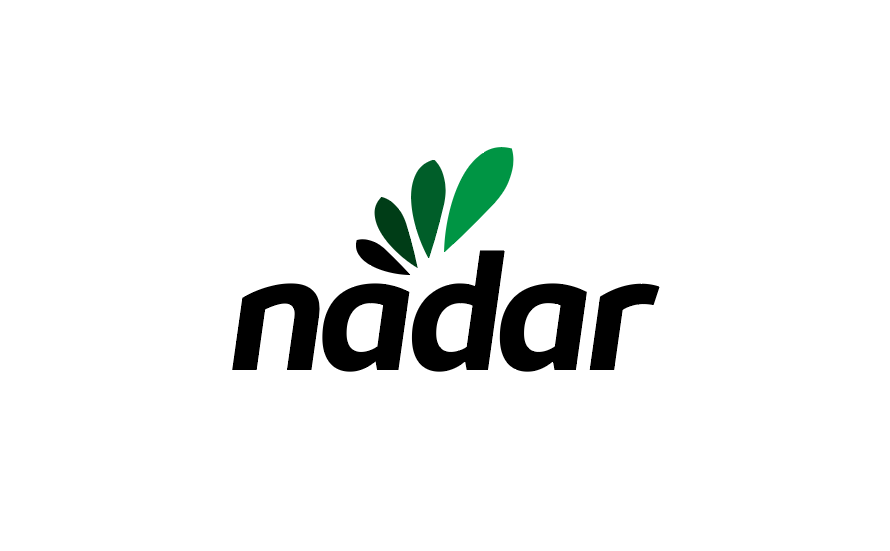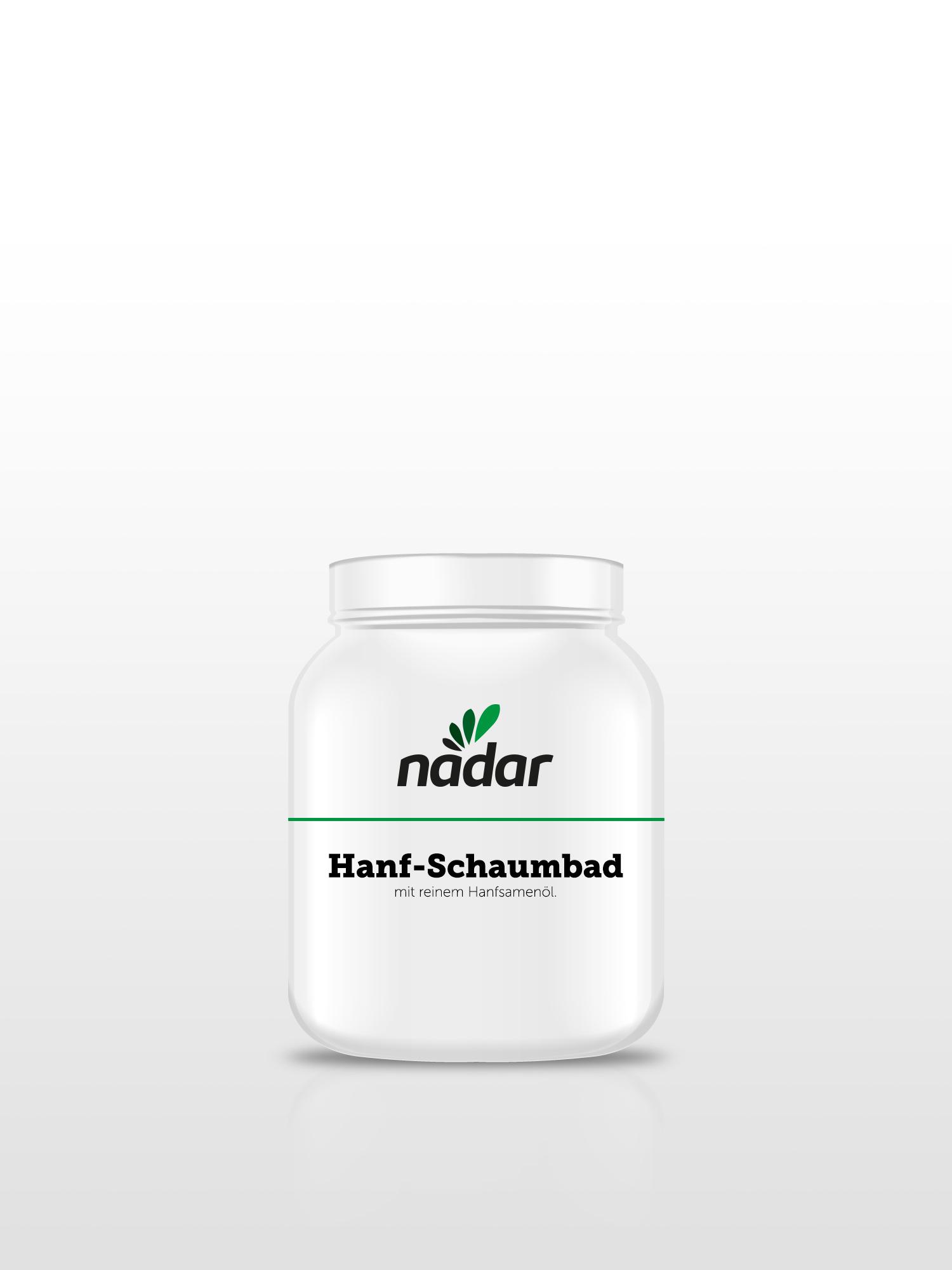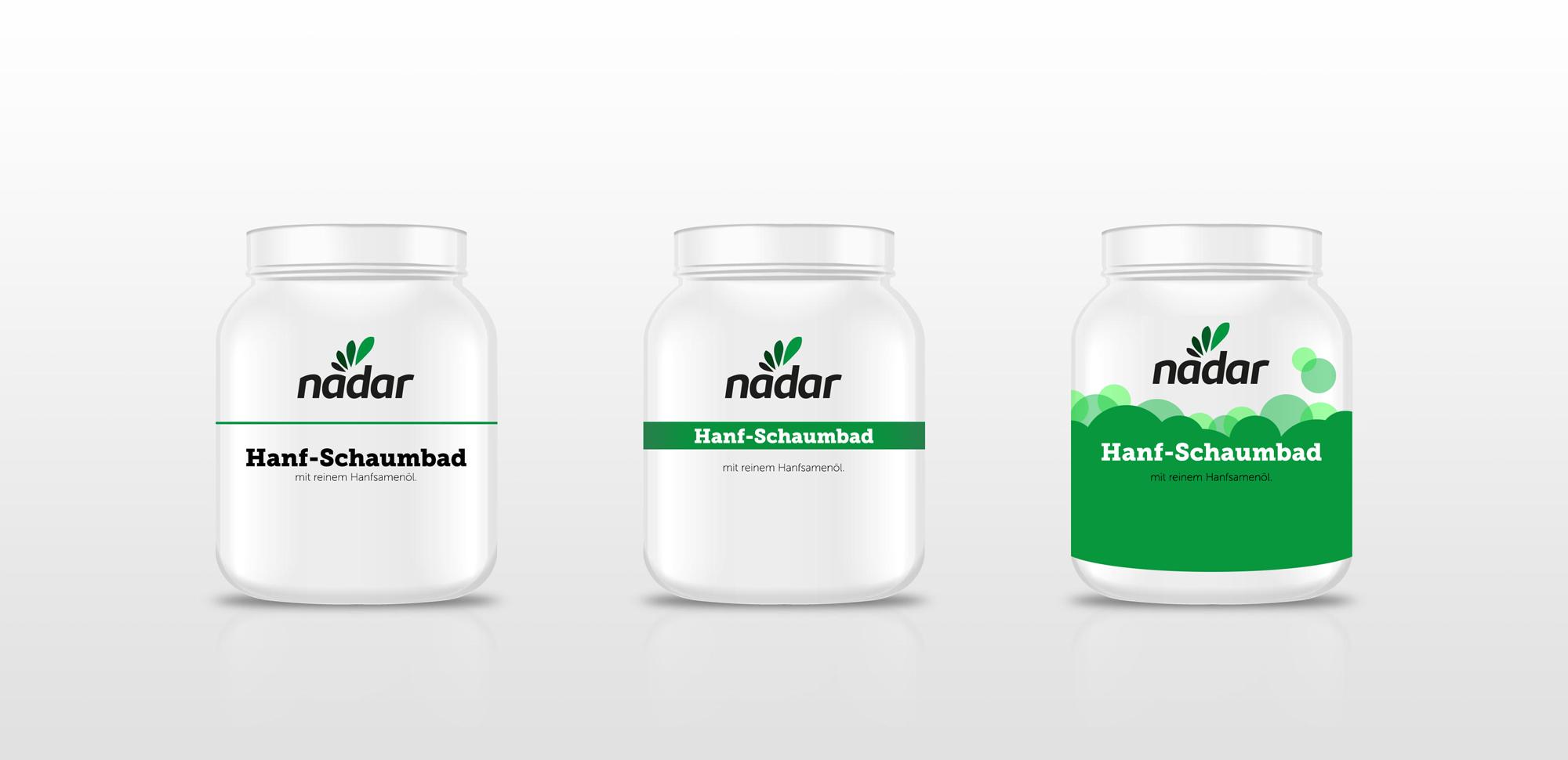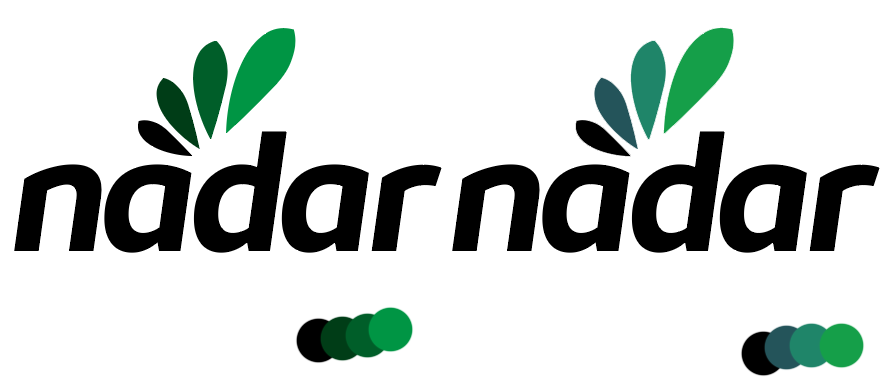
Suche eine mutige aber stimmige Ergänzung zu einem Logo
Ich suche eine passende Gebrauchsschrift zu meinem Logo-Entwurf. Ich würde gerne etwas mutiges nehme, bin mir aber nicht sicher ob ich nicht über das Ziel hinausschieße und meine Idee einfach nur schrecklich ist? ;-)
Die Schrift im Logo ist "Kabrio Bold Italic".
Mein Gedanke war jetzt, für Produktnamen der Firma, die Museo Slab Serif zu verwenden ... und für alles andere die Museo Sans.
Ich bin mir jetzt nicht mehr sicher ob ich mir die Museo nicht "schön geschaut" habe und würde mich über Feedback oder Alternativvorschläge freuen.
Aus vielen, vielen Verpackungen habe ich immer wieder gelernt, dass eine schmallaufende Schrift auf runden Behältnissen wesentlich glücklicher macht. Du kannst ja immer nur einen Ausschnitt unverzerrt lesen, und dieser ist wesentlich kleiner als von dir dargestellt. Mit einer so breiten Slab musst du die Schriftgröße zu klein wählen oder hast Umbrüche im Produktnamen.
Ich empfinde die Kombination  auf den 1., den 2. und den 3. Blick als sehr stimmig.
Ob und wie das auf Verpackungen funktioniert wird man eh probieren müssen. Die häufig verwendeten schmallaufenden Schriften für Kosmetikprodukte empfinde ich als schlecht les- und damit das Produkt als schlecht identifizierbar.
Die Museo kann ich auf Anhieb erkennen und lesen (auch ohne meine PC-/Lesebrille bemühen zu müssen). Und selbst wenn nur ein Teil des Produktnamens auf Anhieb sichtbar ist, steht das Produkt doch entweder in einem Warentypumfeld (Baden/Duschen) oder in einem Markenregal (nur nadar-Produkte) - ein kleiner Griff und ich weiss, worum es sich im Detail handelt.
Wenn diese klare Gestaltung für alle Produkte beibehalten wird, ist es für mich als Käufer kein Problem, in einem Drogeriemarkt z.B. »mein« Duschbad in kürzestmöglicher Zeit zu finden.
Bei mir hat es nur bis zum zweiten Blick standgehalten ;-)
Wobei ich mir nicht sicher bin, ob sich die beiden Schriften beißen oder ich ein Schaumbad nicht mit schwarzer, fetter Slab Serif zusammenkriege ..?
Vielleicht aber auch, weil beide Ebenen – Logo und Produktbezeichnung – schwer und fett sind, aber dann doch wieder anders. Wobei ich nicht empfehlen würde die Schrift aus dem Logo zu verwenden. Vielleicht würde schon helfen einen nicht ganz so schweren Schnitt zu benutzen oder das Logo einfach deutlich kleiner einzusetzen, oder nicht beides schwarz :-?
Will sagen: Es muss gar nicht an der Schriftkombi liegen, sondern an der Gestaltung.
Wie zurückhaltend ein Firmenlogo sein kann, sieht man hier:
Ich find es recht schön. Weil ja jetzt nicht allzu bekannt, darf Logo und auch Produktbezeichnung schon eine gewisse Dominanz haben. Aber schwarz würd ich Produktbezeichnung auch nicht machen. Könnt mir vorstellen daß schon einiges geholfen wär sie in dem zweithellsten grün von dem Logo zu setzen.
HANF
SCHAUM
BAD
Sorry, could not resist. :) Ich glaube auch, dass du Probleme auf der zylindrischen Verpackung bekommst, wenn du eine weit laufende Schriftart verwendest. Eine schmalere Schrift würde das Problem lösen und zusätzlich einen stärkeren Kontrast zu der Logo-Schrift bieten.
Zum Logo: mir gefällt es gut. Durch den Akzent hast du eine schlüssige Erklärung zu den Blätt-Elementen, die nicht einfach irgendwo drangepappt werden, wie man es von vielen schlechteren Logos kennt (die z.B. zufällige Kreisausschnitte irgendwo einfügen). Bei den Farben könntest du vielleicht eine dynamischere Palette benutzen, zum Beispiel in den Mitteltönen die Grüntöne stärker ins Blau zu ziehen. Vielleicht sogar den Schriftzug in einem dunklen Farbton anzulegen statt in Schwarz? Das stufenweise mit schwarz abgedunkelte Grün wirkt in meinen Augen etwas schmutzig:nadar.png.6f952029d736d3cfabfbe00eb999586f.png
Ich weiß nicht, wie weit du mit der Gestaltung der Gesamtverpackung bist, aber ich würde deutlich mehr Farbe verwenden. Die dünne grüne Linie wirkt sehr minimalistisch, meine Assoziation ist aber eher: Medikament. Je nachdem, wieviele Produkte es gibt, könntest Du mit Farben oder Mustern deutlich unterscheidbare Verpackungen bauen. "Ich kauf' immer das Grüne von Nàdar":
Ich schweifte etwas ab. :-D
Ist die Packung überhaupt rund? oder eher quadratisch mir abgerundeten Ecke, so irgendwie in der art:
Das, zusammen mit cdem Ur-Entwurf lässt dann hatürlich den gedanken an Laborbedarf aufkommen, aner auch "extrem reines Zeug"
Ich glaube, es ging zunächst nur um die Frage der Stimmigkeit zwischen Logo und Schrift. Die erste Abbildung war ja nur beispielhaft. Ich glaube, das Problem der zylindrischen Verpackungen mit breitlaufender Schrift gibt es so nicht. Wie ich oben schon erwähnte, die ganzen Schmalläufer (Gestaltungsgesetz: Zylindrisch=automatisch schmale Schrift) sind i.d.R. nicht gut und auf Anhieb lesbar. Ob man letztendlich einen anderen Schnitt (anstatt Museo 900 die 700 oder gar 500) benutzt, muss ja noch anhand der verschiedenen verpackungen geprüft und ausgetüftelt werden.
Also ich glaube ich werde bei "meiner" Museo bleiben ... nicht zuletzt weil es auch serifenlose Schnitte gibt. Die Foral hätte mich auch angelacht, aber da hätte ich dann noch eine weiter serifenlose Schrift kombinieren müssen, und das wird meinem Bekannten dann auch zu unpraktikabel.